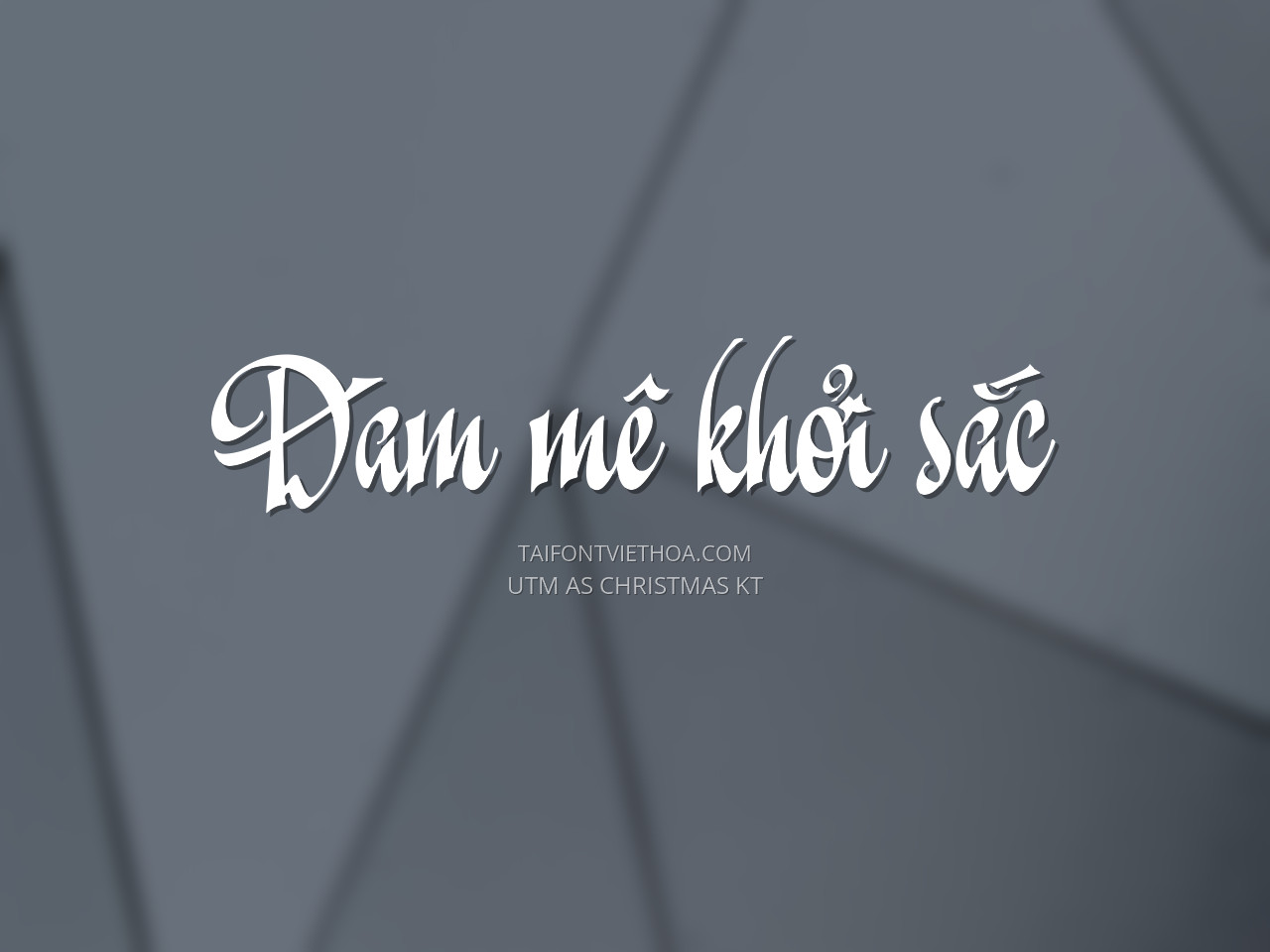
Font việt hóa UTM As Christmas KT
Giới thiệu về font UTM As Christmas KT
UTM As Christmas KT là phiên bản Việt hóa của font As Christmas KT – một kiểu chữ script mang phong cách lễ hội Giáng Sinh ấm áp và vui tươi. Font gốc được thiết kế với các nét chữ bay bổng, mềm mại và đậm chất nghệ thuật, tái hiện không khí lễ hội đặc trưng của mùa đông. Phiên bản Việt hóa đã được hoàn thiện để hỗ trợ đầy đủ tiếng Việt cùng hơn 100 ngôn ngữ khác, giúp font dễ dàng ứng dụng trong các dự án thiết kế mang tinh thần lễ hội.
Đặc điểm thiết kế và ứng dụng của UTM As Christmas KT
UTM As Christmas KT sở hữu cấu trúc script với các nét bút mềm mại, thanh thoát và các ligature đa dạng giúp tạo nên sự uyển chuyển, duyên dáng. Font có độ tương phản nhẹ nhàng, mang lại cảm giác ấm áp và thân thiện, rất thích hợp cho các thiết kế mang phong cách lễ hội và cá nhân hóa cao.
Font phù hợp sử dụng trong các ứng dụng như thiệp mừng Giáng Sinh, thiệp chúc Tết, thiết kế bao bì quà tặng, poster lễ hội và các dự án truyền thông sự kiện. Ngành nghề phù hợp gồm: tổ chức sự kiện, quảng cáo, mỹ phẩm, thời trang và nghệ thuật sáng tạo.